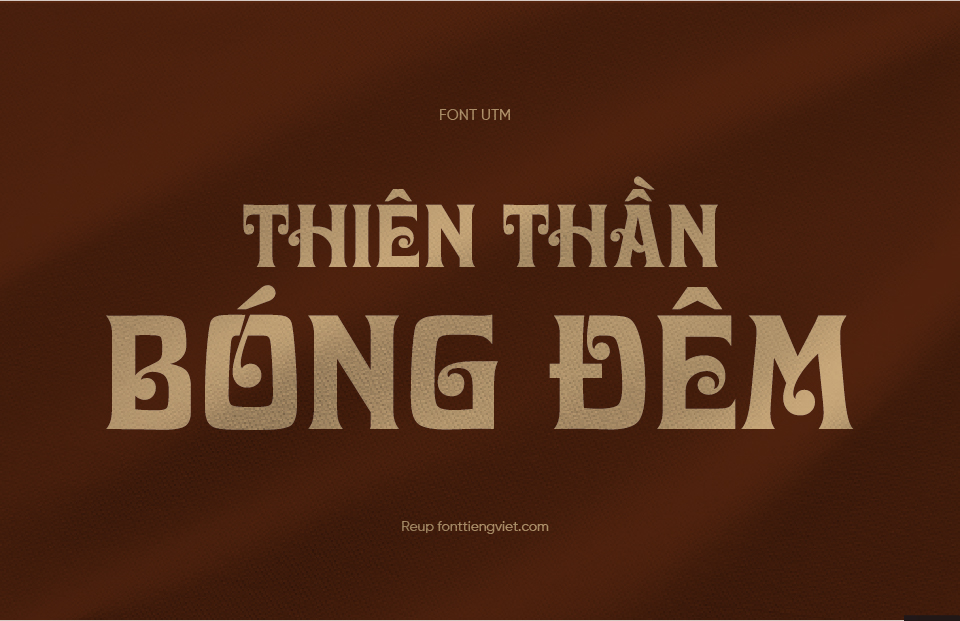
Font việt hóa UTM Davida – Lựa chọn tinh tế cho thiết kế đồ họa học đường
Giới thiệu về Font việt hóa UTM Davida
Trong thế giới đồ họa hiện đại, việc tìm kiếm một bộ Font Chữ vừa mang nét cổ điển vừa giữ được sự sang trọng là điều không hề dễ dàng. Font việt hóa UTM Davida chính là giải pháp hoàn hảo cho các nhà thiết kế tại Việt Nam. Đây là bộ phông chữ thuộc họ Slab Serif với những đường nét cứng cáp, điểm xuyết các chi tiết uốn lượn tinh xảo, giúp tạo nên điểm nhấn thị giác mạnh mẽ. Khi được Việt hóa bởi đội ngũ UTM, các lỗi dấu tiếng Việt hoàn toàn bị loại bỏ, mang lại trải nghiệm sử dụng mượt mà trong mọi ứng dụng văn phòng và đồ họa chuyên nghiệp.
Ưu điểm nổi bật của bộ Font việt hóa UTM Davida
Thiết kế độc đáo và linh hoạt
Đặc điểm nhận diện lớn nhất của Font việt hóa UTM Davida là cấu trúc chữ cái đậm nét và những đường chân trang trí lạ mắt. Phông chữ này rất phù hợp để làm tiêu đề sách, bìa tiểu luận hoặc các ấn phẩm truyền thông trong nhà trường. Sự kết hợp giữa vẻ đẹp truyền thống và tính ứng dụng cao giúp các bạn học sinh dễ dàng sáng tạo các slide thuyết trình ấn tượng mà không lo bị lỗi font.
Khả năng tương thích tốt
Kết luận và cách sử dụng hiệu quả
Việc ứng dụng Font việt hóa UTM Davida vào các dự án thiết kế không chỉ nâng cao tính thẩm mỹ mà còn thể hiện sự chuyên nghiệp của người thực hiện. Để đạt hiệu quả cao nhất, bạn nên kết hợp font này với các kiểu chữ không chân (Sans-serif) đơn giản cho phần nội dung nhằm tạo sự tương phản. Hãy tải ngay bộ Font Miễn Phí, Font Việt Hóa, Font việt hóa UTM Davida để làm mới bộ sưu tập tài nguyên thiết kế của mình ngay hôm nay.